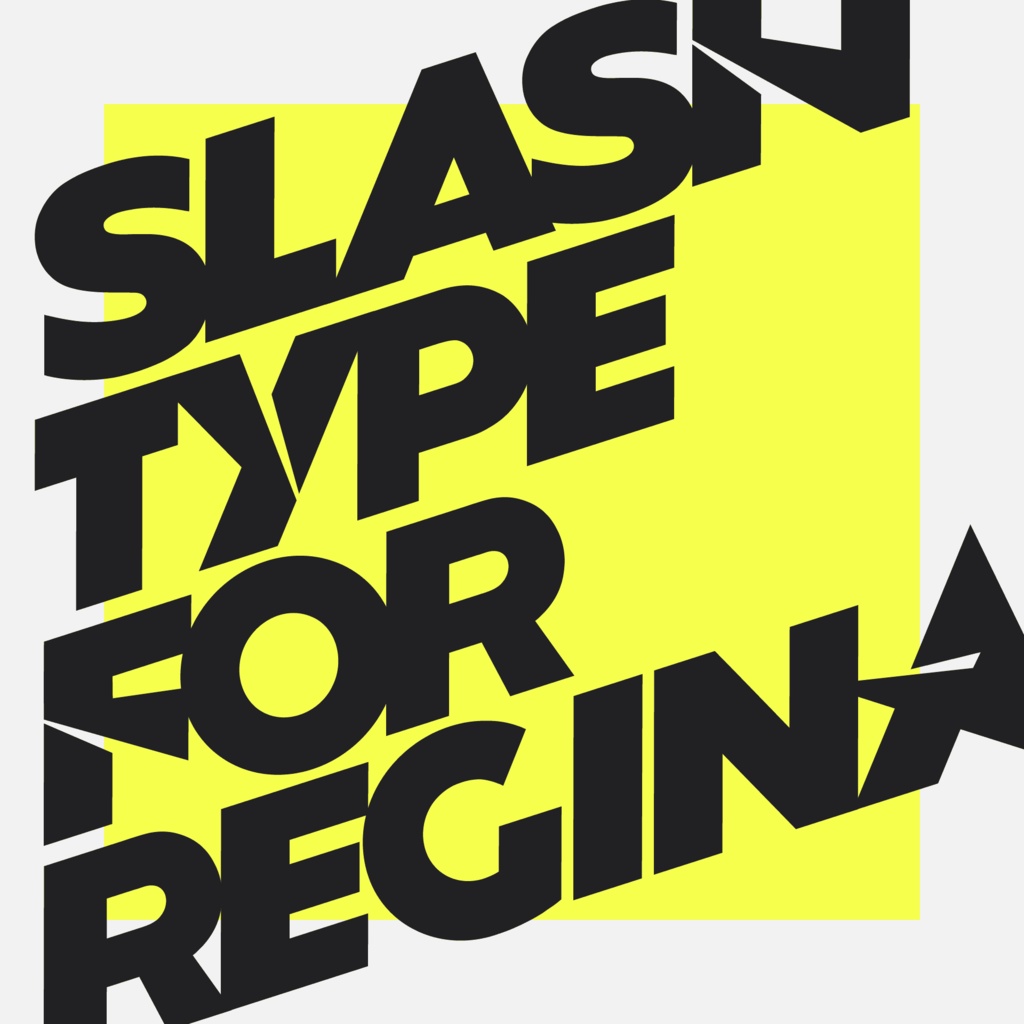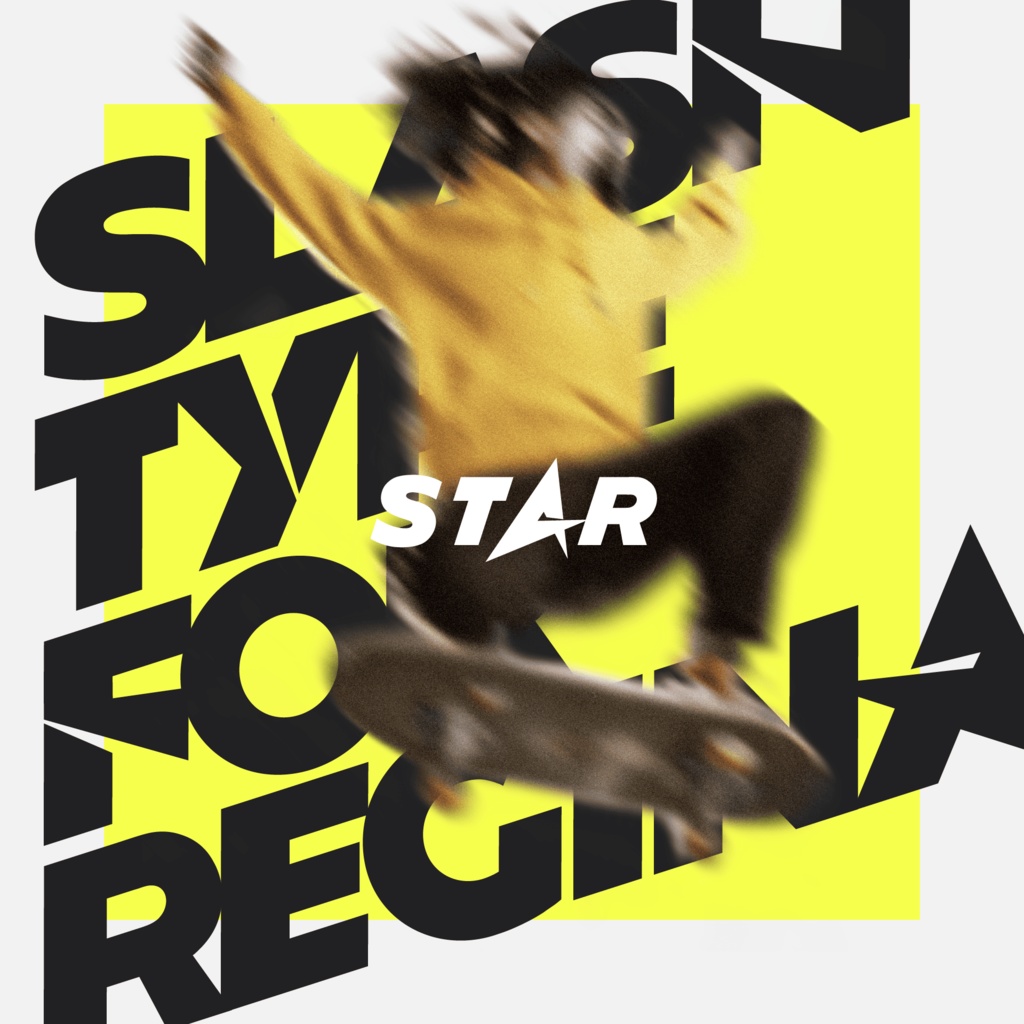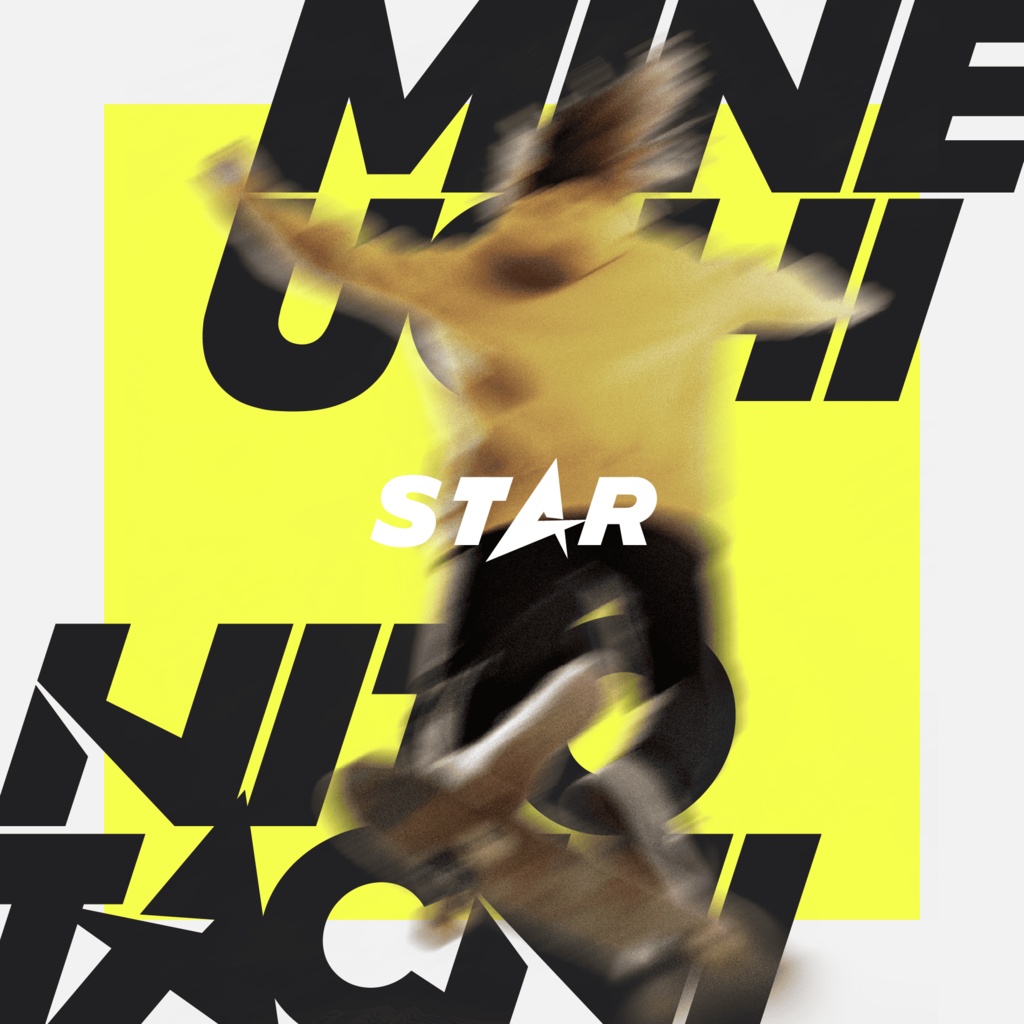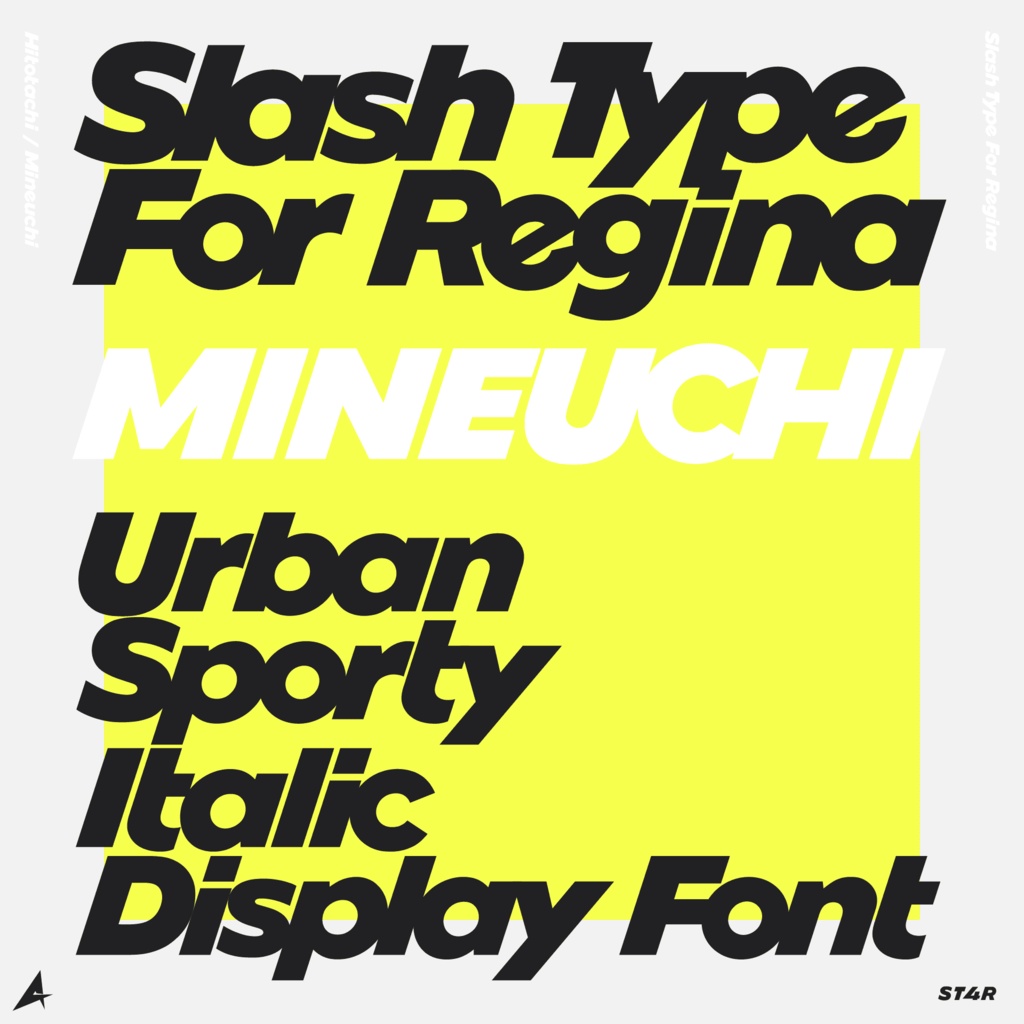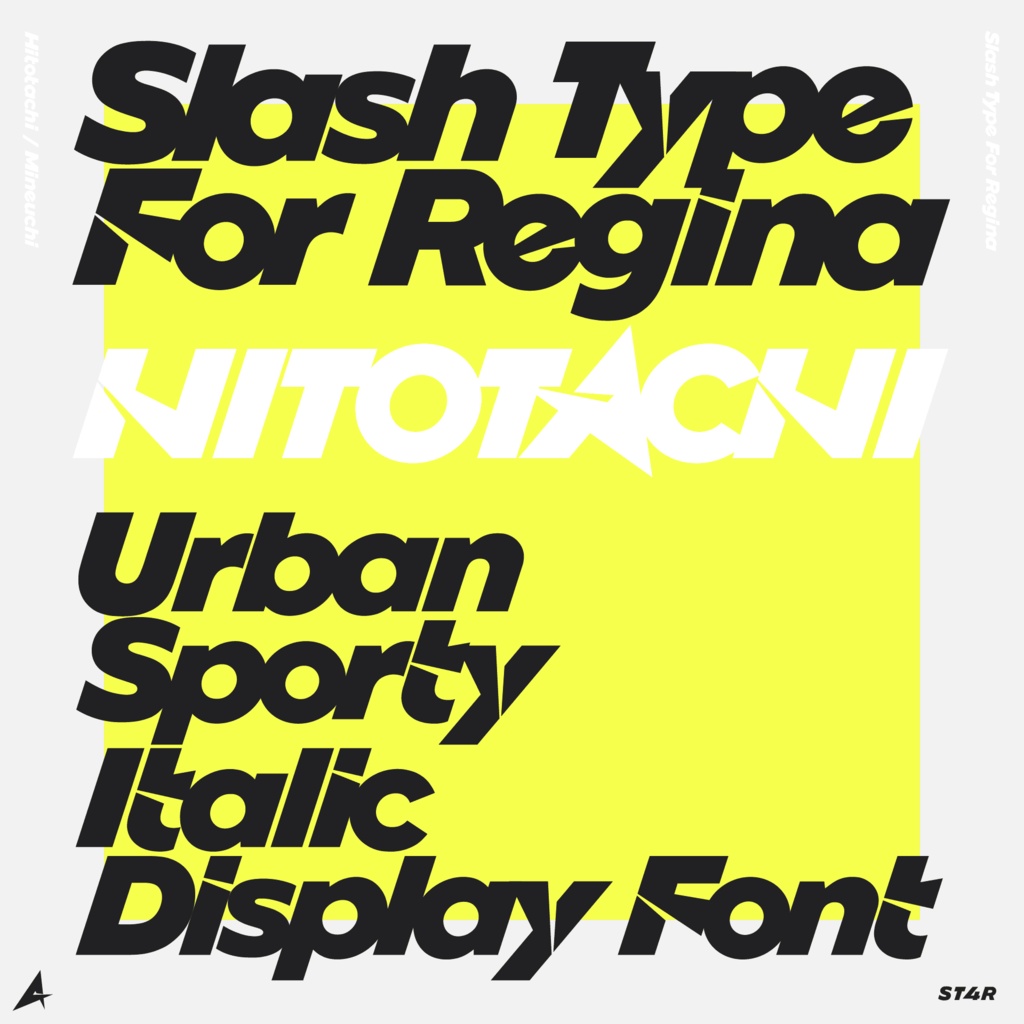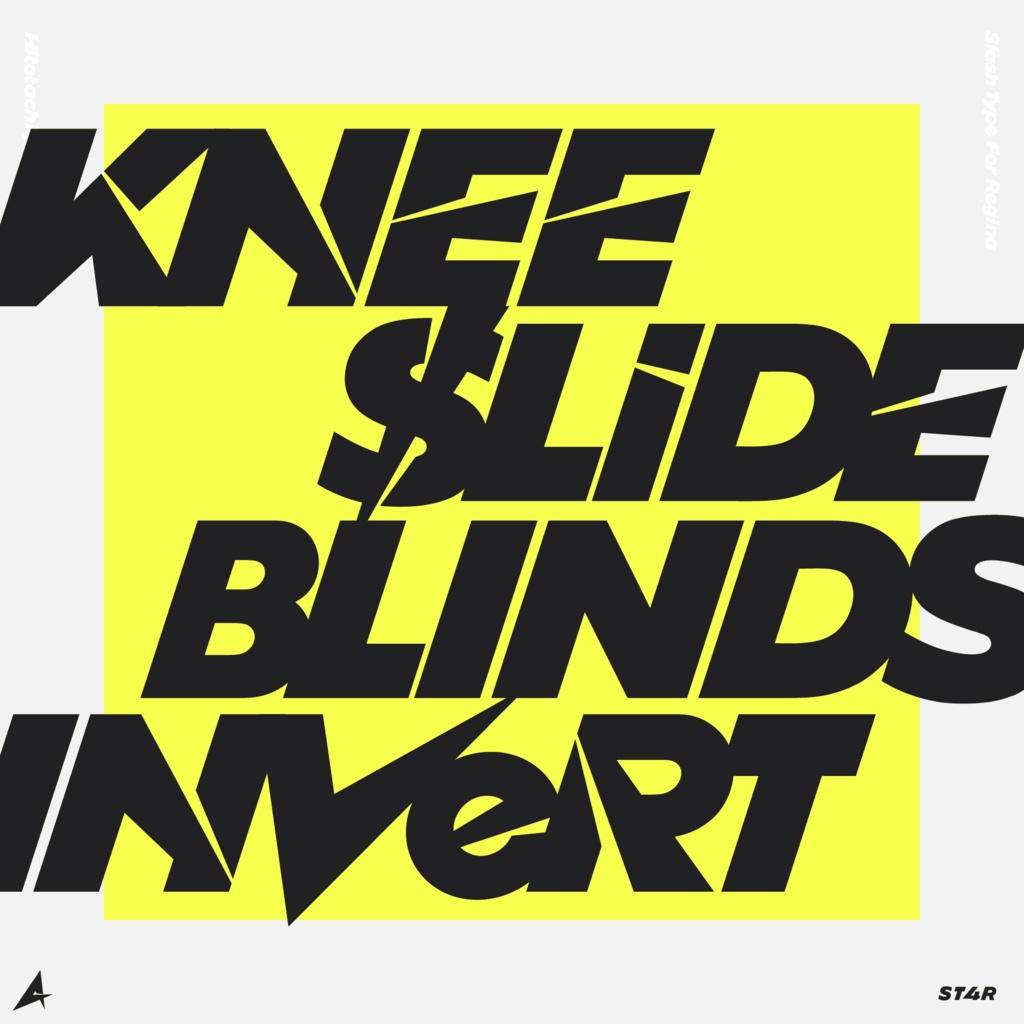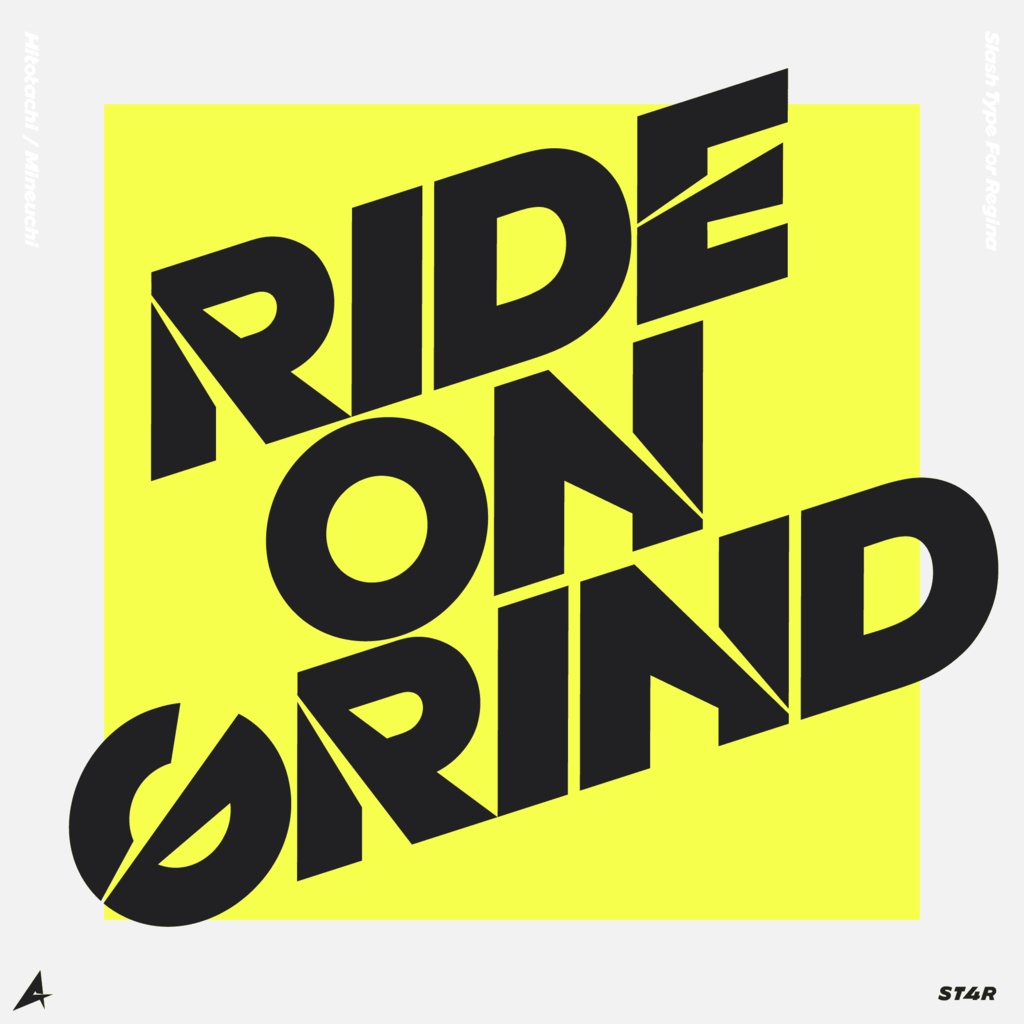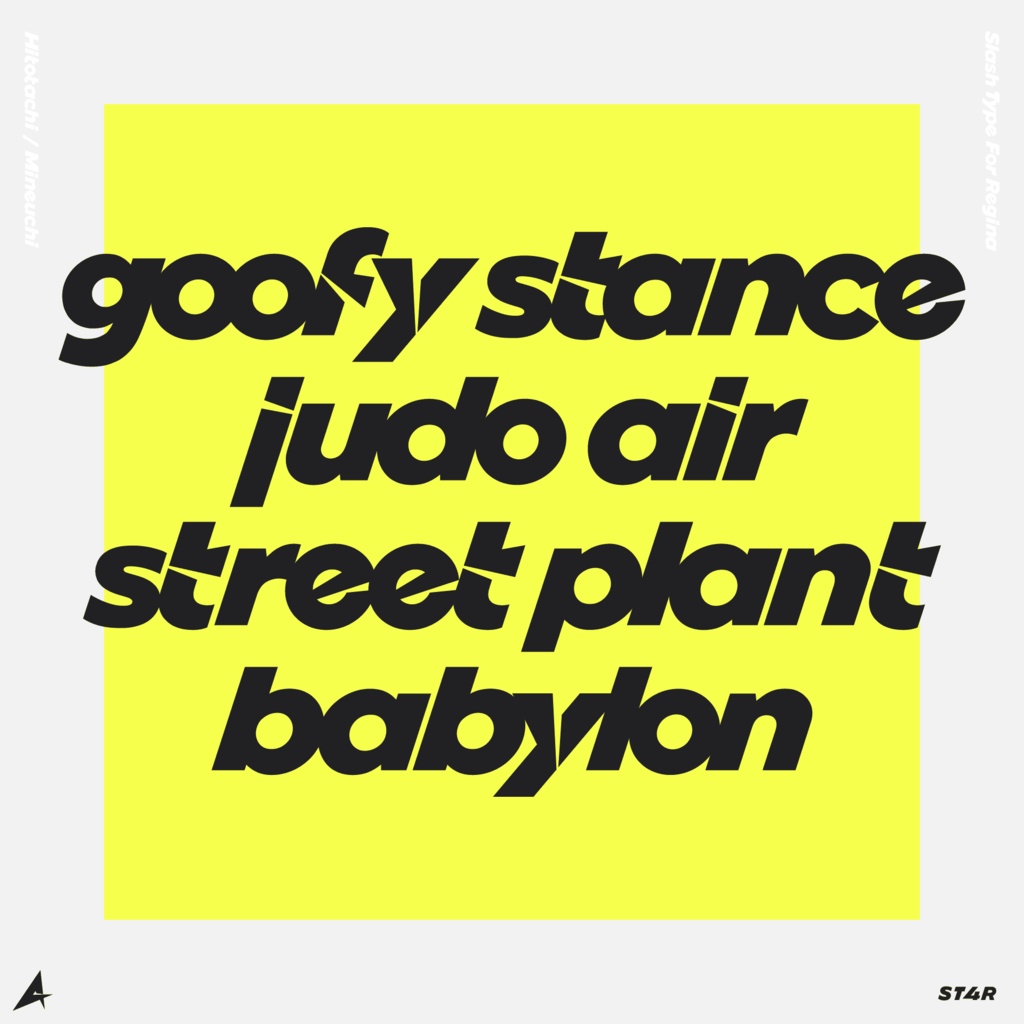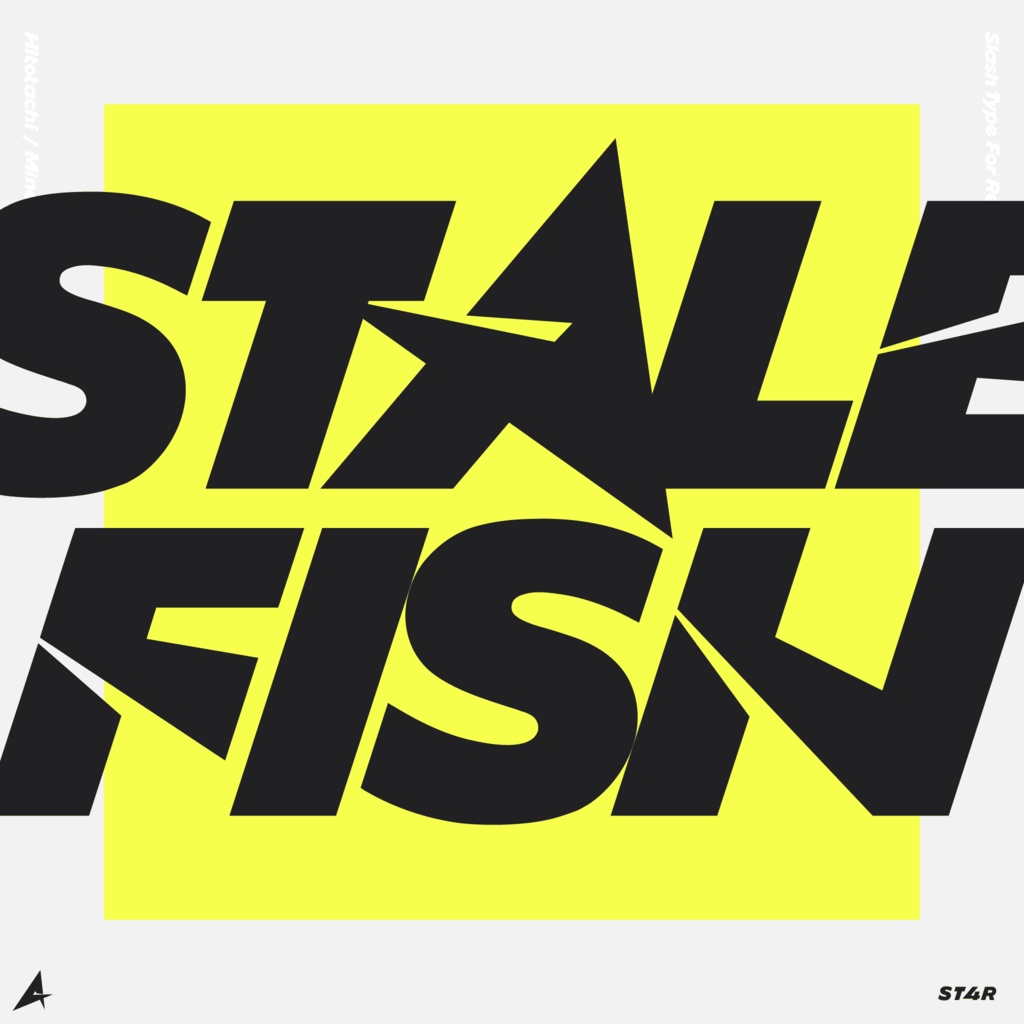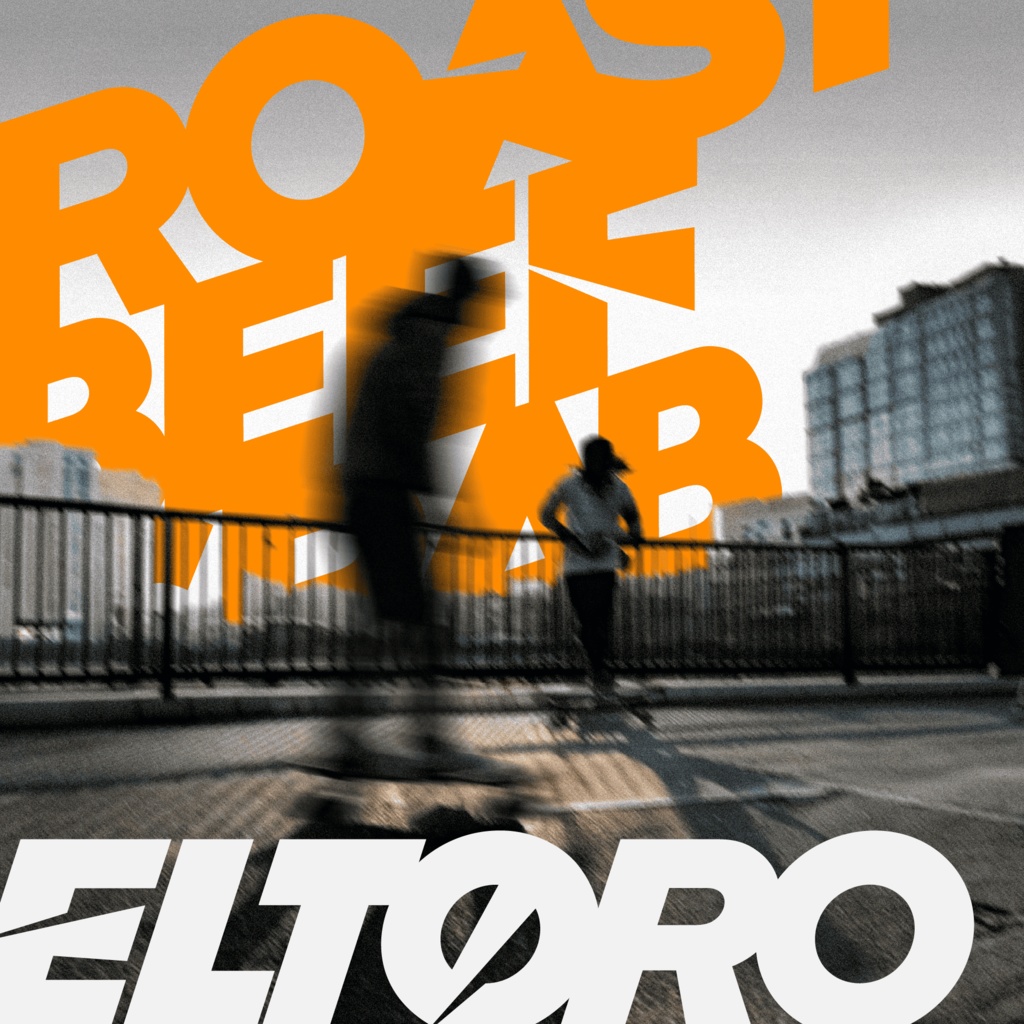
欧文フォントファミリー「Slash Type For Regina」 | Slash Type For Regina Font Family
半角英数字を収録したOpenType(otf)形式のフォントファミリー「Slash Type For Regina」です。 刃物で鋭き切りつけたのような意匠が入った字形の「Hitotachi」、その意匠のないシンプルな字形の「Mineuchi」の2つのフォントが含まれています。 ------------------------------- Slash Type For Regina is an OpenType (OTF) font family. It includes two fonts: Hitotachi, featuring sharp, blade‑like letterforms, and Mineuchi, offering simple and clean shapes without the decorative cuts. A detailed English description is provided below. ------------------------------- □ 更新情報 - 2025年10月21日: スペースの幅を変更しました。 □ 使用範囲 - 商用利用可能 印刷物、Webサイト、動画などにご利用ください。 使用報告、クレジット表記などは必要ありません。してくれてもいいけどね - 1回の購入につき、独占的に使用しているデバイス1台まででの使用を許可します。複数台で使用したい場合は台数分のライセンス購入が必要です。 - プログラムに組み込む場合はフォントデータの吸い出しが困難な仕様にしてください。 - フォントデータの改変を許可します。ただし本製品を元にしたデータ自体の配布・販売は禁止です。 □ 注意事項 - 独学で試行錯誤しながらフォントを制作しています。製品としての品質には気を配っていますが、ミスや不具合がないとは言えません。 - データのアップデートがあった場合、最新のバージョンに差し替えて販売を継続します。 - OpenTypeフォントは、一部の古いソフトなどでは利用できないことがあります。使いたいソフトがOpenTypeに対応しているか確認してから購入してください。 - 一部製品では文字間の隙間が自動で調整されるようにつくっています。対応するソフトでのみ適応されます。 - 一部製品では合字、異体字を用意しています。対応するソフトでのみ利用できます。 - Windowsでのメモ帳、Adobeソフト上での動作のみ確認しています。その他の環境での動作確認は行っておりません。 □ 禁止行為 - 本製品および本製品を改変したデータそのものを配布、販売すること。 - バックアップ以外の目的でいたずらにフォントデータを複製すること。 - ライセンスの譲渡および購入者以外が本製品を利用すること。 - 本製品を利用し作られた制作物の知的財産権の登録をすること。 - 悪意を持って誰かを傷つける行為に本製品を使用すること。 □ 免責事項 - 本製品の利用や利用に関連することで購入者が損害を被ったとき、いかなる場合でも私は一切の責任を負担しません。全て自己責任で利用してください。 本ファイルは武蔵システム(https://opentype.jp/)のOTEditを使って作成しました。 □ クレジット デザイン・開発:Tabun https://x.com/tabun_mojimoji https://tabun-mojimoji.booth.pm/ © 2024 Tabun All rights reserved. ------------------------------- □ Update Information - October 21, 2025: Adjusted the width of the space character. □ Usage Terms - Commercial use is allowed. You may use this font in printed materials, websites, videos, and more. No usage report or credit is required, though it is appreciated. - A single license allows installation on one device only. For use on multiple devices, please purchase additional licenses accordingly. - When embedding the font in software, ensure the font data cannot be easily extracted. - Modification of the font data is permitted; however, redistribution or resale of the modified font file is prohibited. □ Notes - This font was created through self-study and experimentation. While I strive for quality, errors or imperfections may exist. - If the font is updated, the latest version will be used for continued sales. - Some older applications may not support OpenType fonts. Please verify software compatibility before purchasing. - Certain fonts automatically adjust letter spacing or include ligatures and alternate glyphs, which are available only in compatible applications. - Testing has been done only on Windows Notepad and Adobe applications. Other environments are not verified. □ Prohibited Actions - Redistribution or sale of the original or modified font files. - Unnecessary duplication of font data for purposes other than backup. - Transfer of license or use of the font by anyone other than the original purchaser. - Registering intellectual property rights for works created with this font. - Using this font for malicious or harmful purposes. □ Disclaimer - The creator assumes no responsibility for any damages resulting from the use of this product. Use at your own risk. This font was created using OTEdit by Musashi System (https://opentype.jp/). □ Credits Designed and developed by Tabun. https://x.com/tabun_mojimoji https://tabun-mojimoji.booth.pm/ © 2024 Tabun All rights reserved.